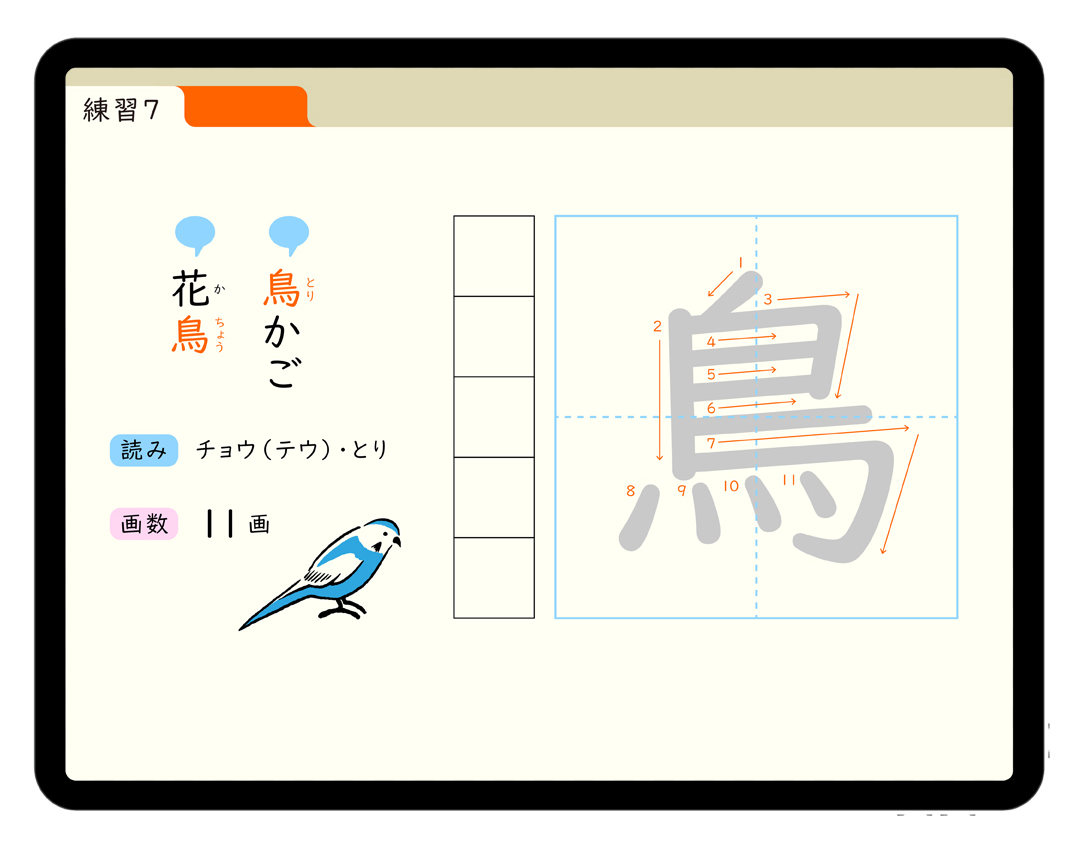
「UDデジタル教科書体」について
2018年に登場したUDデジタル教科書体は、ユニバーサルデザインフォントです。ロービジョン(弱視)やディスクレシア(読み書き障害)に配慮して、「より多くの人に読みやすい教科書体」として誕生しました。デザイナーの想像だけでなく、しっかりと当事者の現場の声を聞きながら開発されています。
「UDデジタル教科書体」の特徴
電子黒板やデジタル教科書など、ICT教育に適したフォントです。教科書体として学習指導要領に準拠した字形を採用しつつ、見やすさのポイントの1つとなる一定の線の太さを保ちながらも、正しく運筆が分かるように設計されています。
読み手によってはストレスになることもある文字のエレメントの強弱・抑揚を抑えながらも、画数や形状は手書きに近いという考え抜かれたフォントです。楷書ではなく硬筆やサインペンの文字が意識されています。
また、同書体は書き順に沿ったストロークごとに一文字として、文字を書いていく過程(描画)を収録した筆順フォントが別に用意されています。
従来の一般的な教科書体とゴシック体のウイークポイントが両方カバーされ、現代の教育の現場に最適なフォントです。作例はiPadで表示する教材を想定しています。文字の線を書く方向も分かりやすく、まさにデジタル時代の新しい教科書体といった印象です。